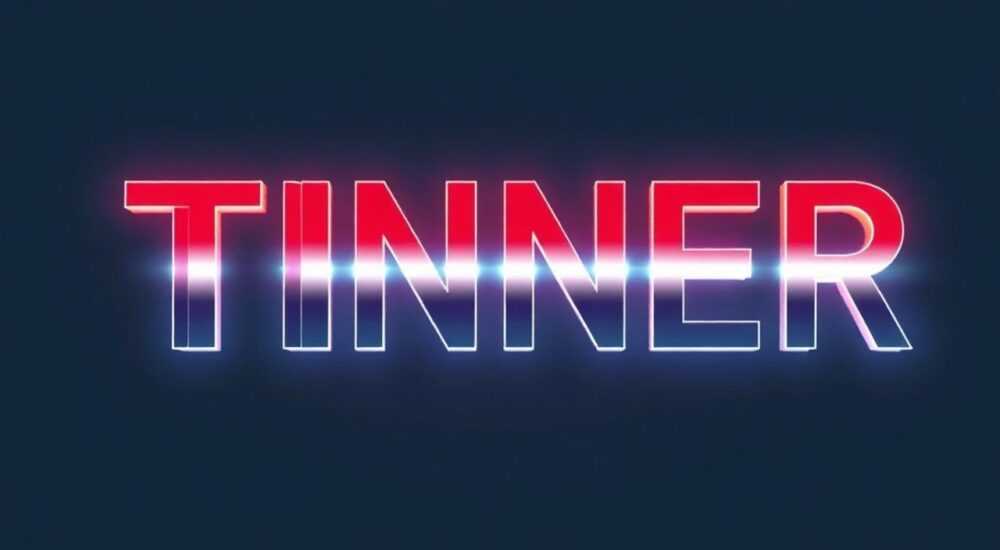
Как сделать шрифт в фотошопе тоньше
В дизайне текст — это не просто набор букв, а мощный инструмент визуальной коммуникации. Часто при работе с типографикой в Adobe Photoshop возникает задача: как сделать шрифт тоньше, чтобы он выглядел изящнее, современнее или лучше вписался в композицию. Проблема актуальна как для новичков, так и для опытных дизайнеров, особенно когда нужный тонкий начертание шрифта отсутствует в семействе. К счастью, в Фотошопе есть несколько эффективных способов достичь желаемого эффекта — от изменения параметров обводки до использования векторных масштабирований и внешних плагинов.
Зачем делать шрифт тоньше: практические причины и дизайн-задачи
В современном графическом дизайне лёгкость и воздушность текста часто становятся ключевыми элементами эстетики. Тонкие шрифты используются в логотипах, заголовках, постерах, веб-дизайне и социальных сетях. Они создают ощущение изысканности, технологичности и минимализма. Однако не всегда доступно нужное начертание — например, Light или Thin. В таких случаях дизайнеру приходится имитировать тонкое начертание, используя возможности редактора.
Тонкие шрифты особенно популярны в брендинге премиум-сегмента: мода, ювелирные изделия, технологии. Они хорошо читаются на светлом фоне и добавляют композиции «воздух». Но важно понимать: искусственное утончение может повлиять на читаемость и качество восприятия. Поэтому подход должен быть продуманным.
Иногда задача утончения возникает из-за технических ограничений. Например, клиент предоставил логотип с текстом в жирном шрифте, но просит его «сделать изящнее». Вместо поиска нового шрифта можно скорректировать существующий. Главное — сохранить узнаваемость и не испортить геометрию символов.
Метод 1: Коррекция через стиль слоя «Обводка»
Один из самых простых и безопасных способов — использование стиля слоя «Обводка» с отрицательным цветом. Суть метода: вы добавляете обводку того же цвета, что и фон, которая визуально «съедает» края текста, делая его тоньше.
Шаги реализации:
- Выделите текстовый слой в панели слоёв.
- Нажмите на значок «fx» внизу панели и выберите «Обводка» (Stroke).
- Установите положение обводки — «Внутри» (Inside).
- Цвет установите в соответствии с фоном (например, белый, если фон белый).
- Размер обводки начните с 1–2 пикселей. Для тонкой коррекции достаточно малых значений.
Преимущество этого метода — не нужно конвертировать текст в кривые. Вы сохраняете возможность редактирования содержимого, размера и начертания. Это особенно важно на этапе правок.
Однако есть ограничения. При слишком большой обводке текст может выглядеть «съеденным» или терять детали — например, засечки или внутренние пробелы. Также метод не работает, если фон неоднородный (градиент, фото).
Плюсы |
Минусы |
|---|---|
Без потери редактируемости текста |
Ограниченная степень утончения |
Подходит для однотонных фонов |
Не работает на сложных фонах |
Быстрое применение |
Может исказить мелкие детали |
Метод 2: Масштабирование по оси X с последующей коррекцией
Ещё один популярный способ — горизонтальное сжатие текста. Хотя это не меняет толщину штриха напрямую, визуально буквы становятся уже и тоньше. Особенно эффективно на sans-serif шрифтах.
Как выполнить:
- Выберите текстовый слой.
- Нажмите Ctrl+T (или Cmd+T на Mac), чтобы активировать свободную трансформацию.
- Удерживая Shift (для сохранения пропорций по высоте), потяните за боковые маркеры, уменьшая ширину на 5–15%.
- Подтвердите трансформацию клавишей Enter.
Ключевой момент — не переусердствовать. Сильное сжатие (более 20%) делает текст неестественным: круглые формы становятся овальными, а пропорции нарушаются. Лучше использовать этот метод как дополнительный — в связке с другими техниками.
Для более точного контроля можно использовать панель «Свободная трансформация» и задать процент вручную. Например, значение ширины 90% даст умеренное сужение без потери качества.
Метод 3: Конвертация текста в векторные контуры
Самый гибкий, но и самый радикальный способ — преобразование текста в фигуры. После этой операции вы получаете полный контроль над контурами каждого символа, но теряете возможность редактировать текст.
Пошаговая инструкция:
- Щёлкните правой кнопкой по текстовому слою.
- Выберите «Создать контуры» (Create Outlines) или «Контуры» (Convert to Shape).
- Теперь текст становится векторной фигурой.
- Используйте инструмент «Перо» (P) или «Прямое выделение» (A), чтобы изменить толщину штрихов.
Теперь вы можете вручную сдвигать узлы, удалять лишние точки или использовать функцию «Обводка» с отрицательным значением. Некоторые дизайнеры применяют фильтр «Сжатие/Растяжение» через меню Edit → Transform → Scale, контролируя только горизонтальную ось.